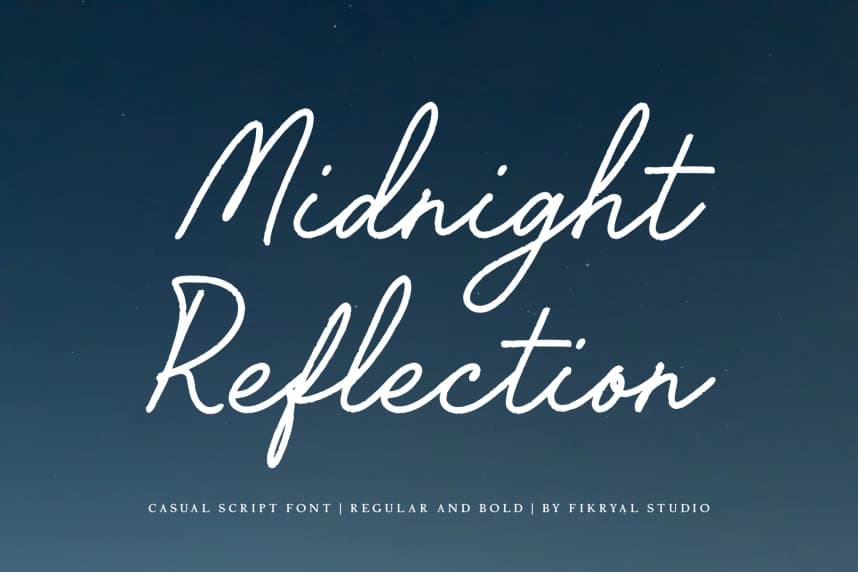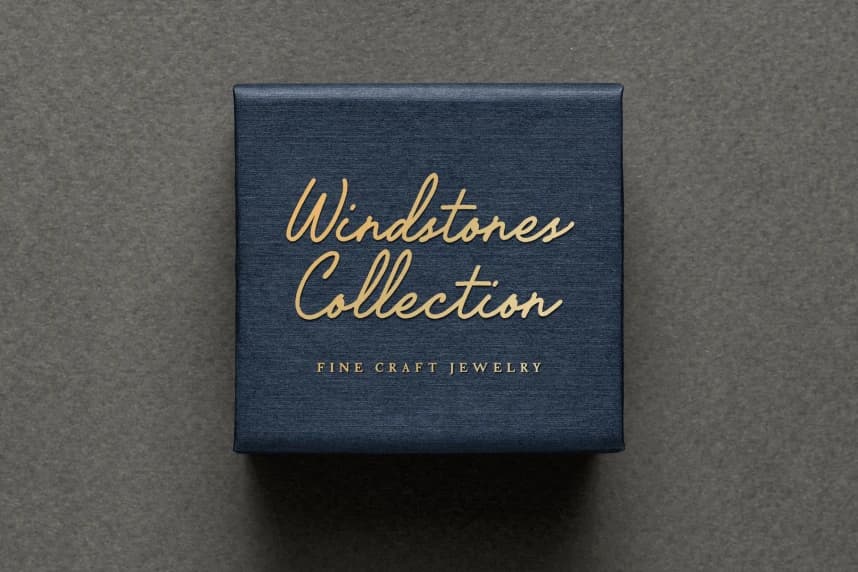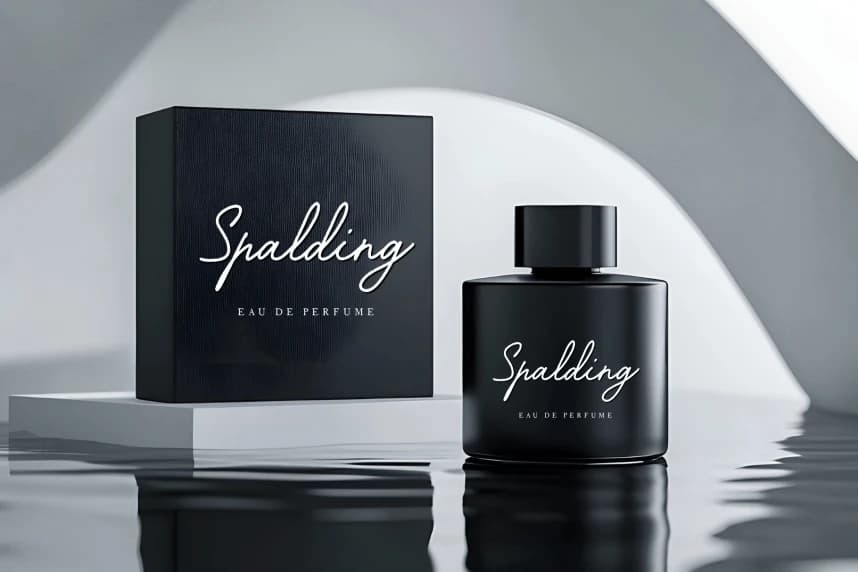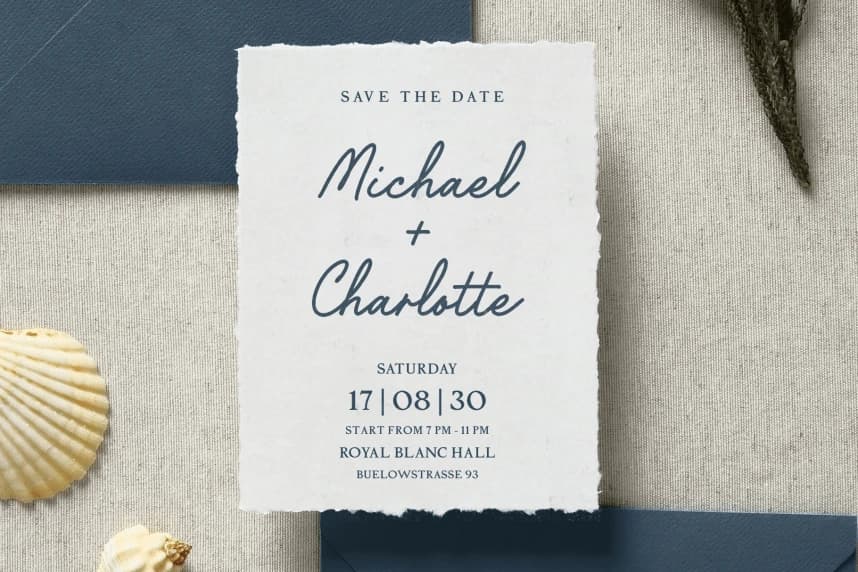
Midnight Reflection – Casual Script Font
Midnight Reflection – Casual Script Font, her tasarıma doğal bir el yazısı fırça hissi katan rahat bir script yazı tipidir. Otantik akıcı çizgiler ve organik fırça dokularıyla tasarlanmış bu yazı tipi, sıcak, ifade gücü yüksek ve vintage esintili bir görünüm yaratır; bu görünüm kişisel ve zamansız b
Midnight Reflection – Casual Script Font, her tasarıma doğal el yazısı fırça hissi veren bir gündelik el yazısı fontudur. Gerçekçi akıcı darbeler ve organik fırça dokularıyla tasarlanmış olan bu yazı tipi, sıcak, ifade gücü yüksek ve vintage esintili bir görünüm yaratır; bu da kişisel ve zamansız bir his verir.